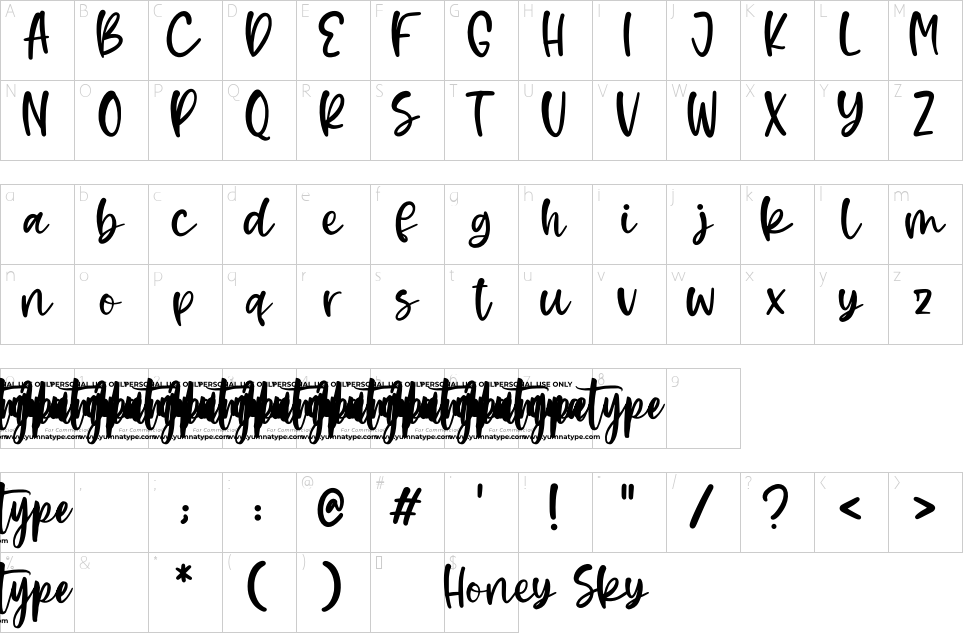
A Honey Sky é uma fonte arrojada e criativa que combina elementos futuristas com nuances românticas, resultando num conjunto visual único para seu projeto. Desenvolvida por Yumna Type, esta fonte conta com um vasto espectro de caracteres que vão desde letras maiúsculas até símbolos especiais, o que a torna uma opção versátil e eficaz tanto para criações digitais quanto para design gráfico em papel. Download gratuito do Windows e Mac, Honey Sky é uma ótima escolha para quem busca personalidade e estilo para seus projetos digitais. Desde letras fortes até ornamentos delicados, a Honey Sky oferece uma paleta de opções que se adequa perfeitamente às suas necessidades de design. Com quase cinco mil downloads no total, é fácil ver por que essa fonte tem atraído tanto interesse e admiração entre os designers.